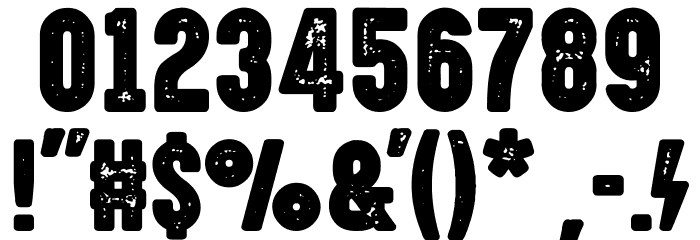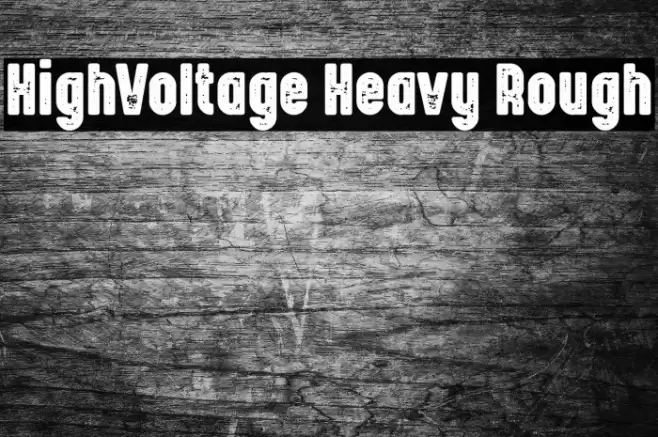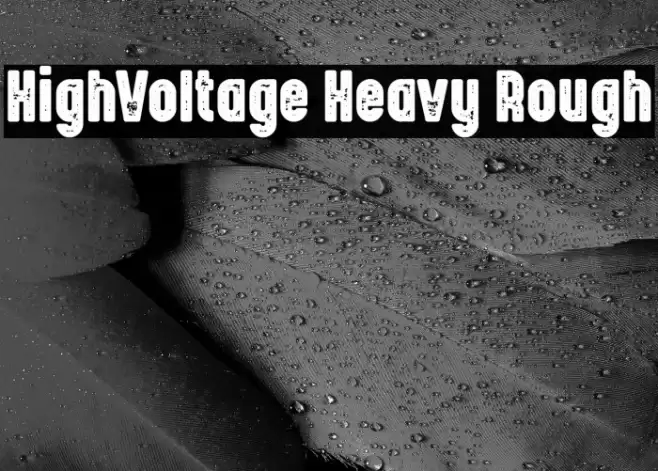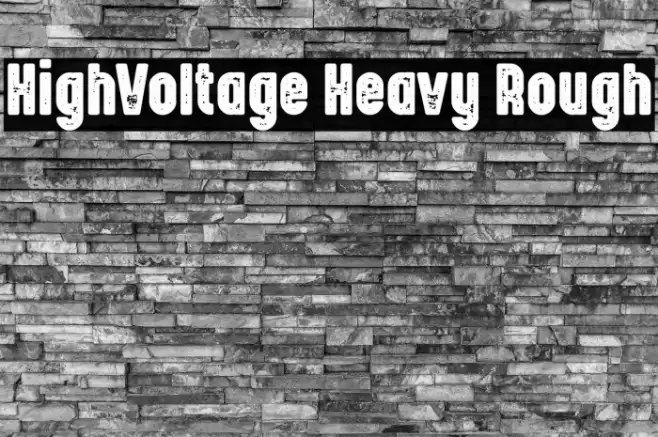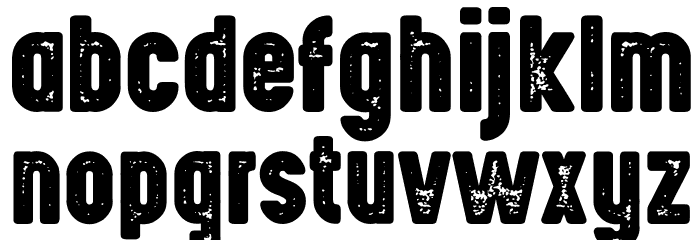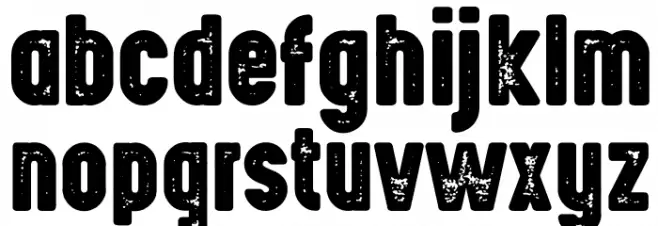
HighVoltage Heavy Rough Font
✎ Messy
| Categorii | Messy |
| Stil general | Vintage, Industrial |
| Proiecte propuse | Ideal for posters, logos, album covers, and any design requiring a bold, vintage, or industrial aesthetic. |